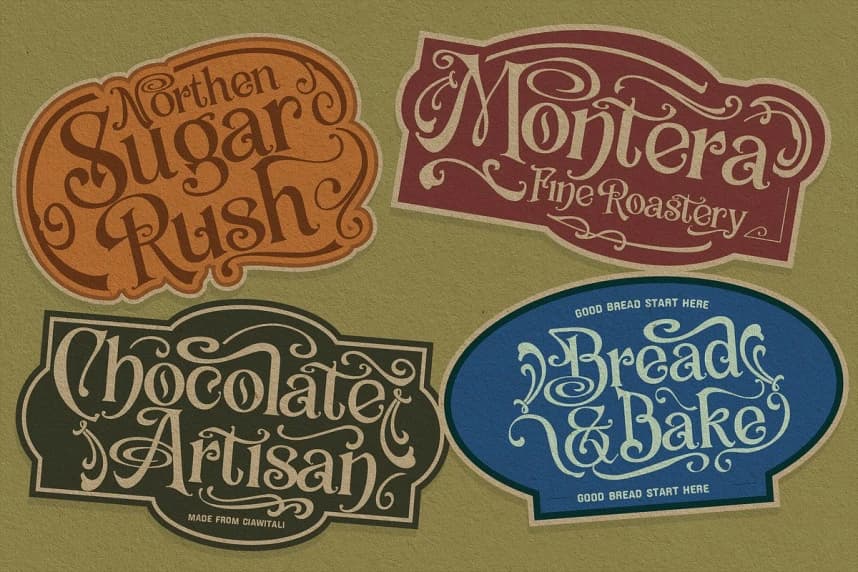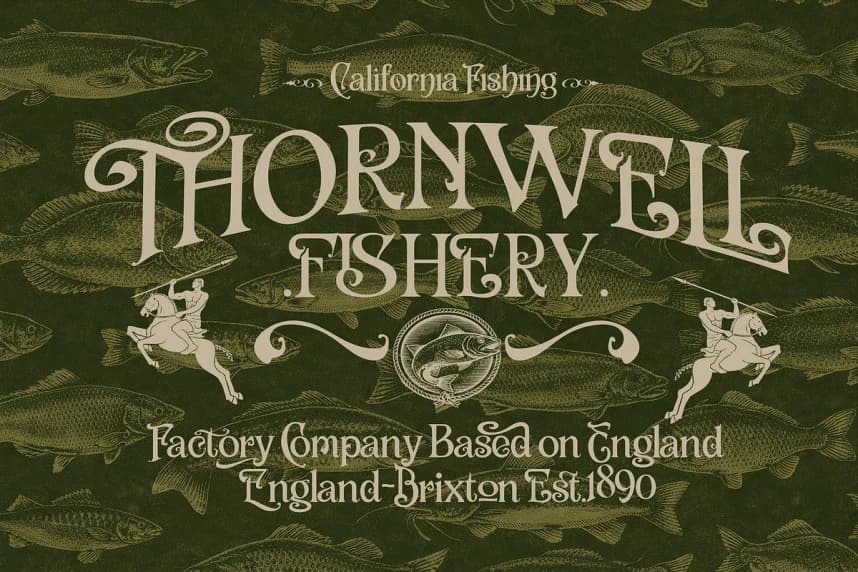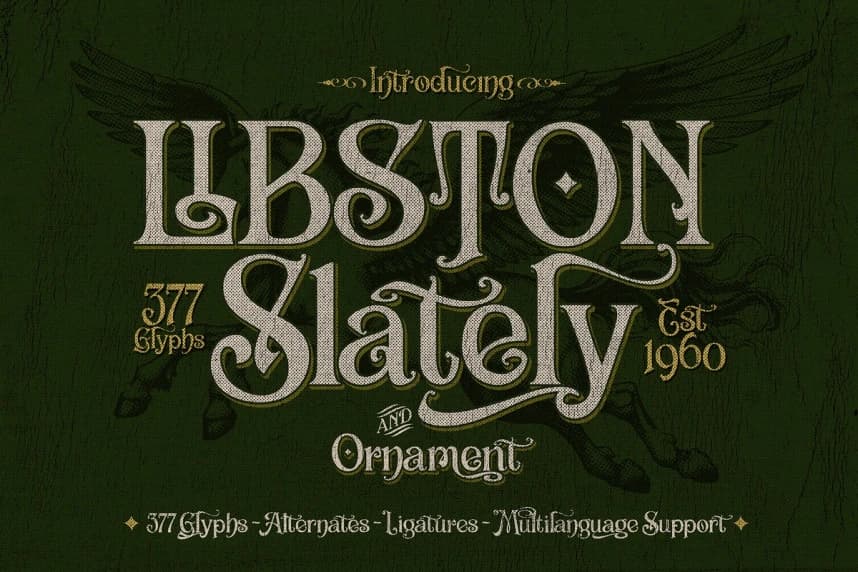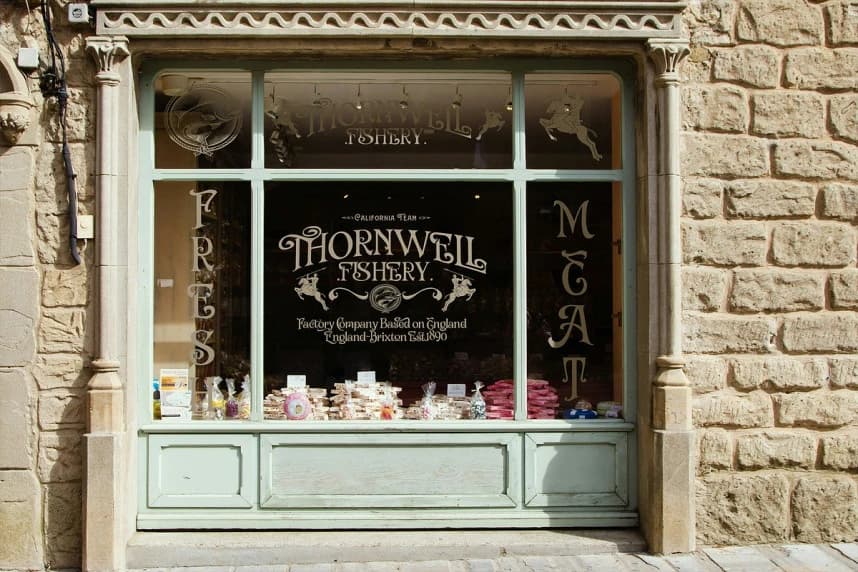
LIBSTON Font, Viktorya mirası ve klasik etiket tasarımından ilham alan vintage bir serif yazı tipidir. Kavislerle, süs detaylarla ve zarif kontrastla tasarlanmış bu yazı tipi, projelerinize zamansız bir zarafet katıyor.
LIBSTON Font, Viktorya mirasından ilham alan vintage bir serif yazı tipidir. Eğrilerle, süs detaylarıyla ve rafine kontrastla tasarlanmıştır; bu font projelerinize zamansız bir zarafet katar.